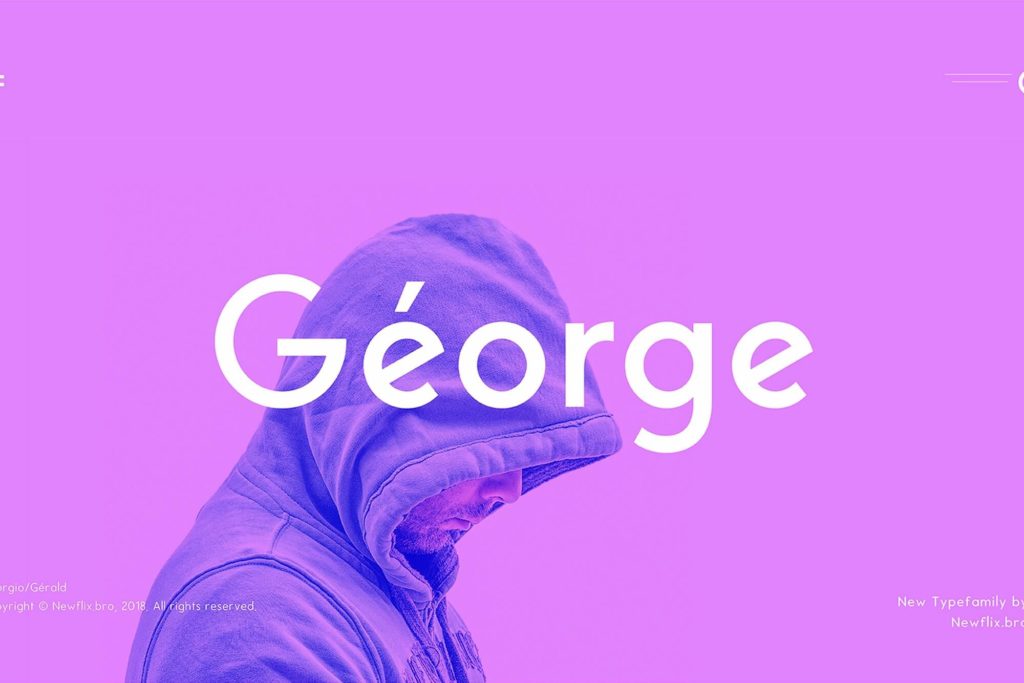
Шрифт George Sans Geometric Typeface
это элегантный геометрический гротеск от студии Kaligra.co, отличающийся чистыми линиями и строгой современной геометрией. Шрифт обладает гармоничным начертанием букв, которое делает его отличным выбором как для заголовков, так и для основного текста. В оригинальной версии представлено 8 начертаний, включая полужирные и курсивные варианты. Данная версия адаптирована для корректного отображения кириллицы, сохраняя визуальную целостность стиля. Если вы ищете современный шрифт для айдентики или веб-дизайна, вы можете скачать бесплатно этот набор начертаний на нашем сайте.